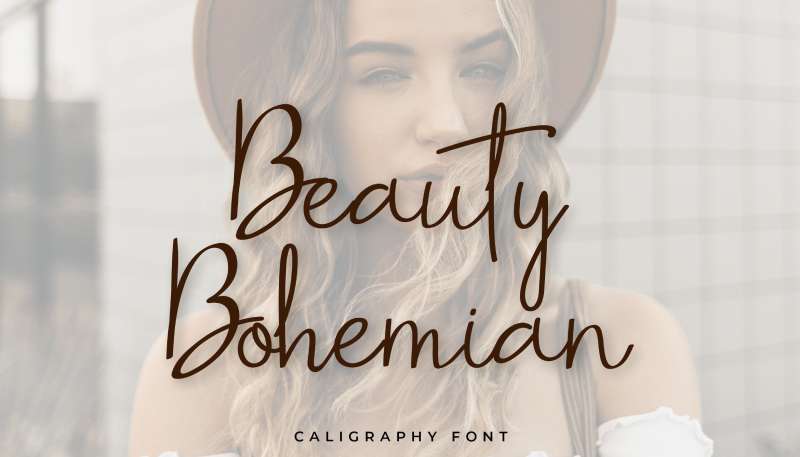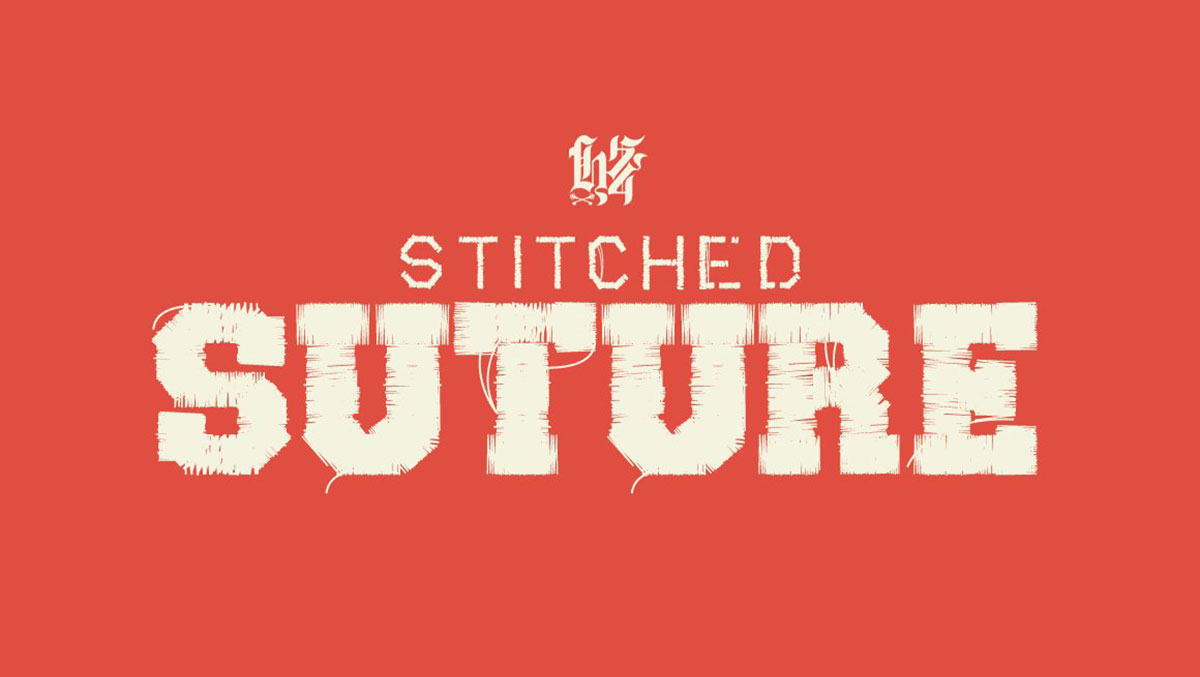
Stickerei verwandelt das Gewöhnliche in Kunst; der richtige Faden, ein Hauch von Kreativität, und voilà, ein Meisterwerk eingraviert in Stoff.
Aber was haucht wirklich Leben in Ihre Stickarbeiten ein? Die besten Schriftarten für Stickereien. Sie sind nicht nur Buchstaben; sie sind die stillen Botschafter Ihrer Marke, die unausgesprochenen Erzähler Ihres Handwerks.
In diesem Schatz an Texten liegt ein Rätsel für Designer – eine Schriftart zu wählen, die die Eigenheiten des Mediums ergänzt.
Ob Sie mit PES-Formaten digitalisieren oder von Hand einfädeln, der Weg vom Bildschirm zum Stoff ist voller Entscheidungen.
Fadengewicht, Spannungseinstellungen, der Stabilisator für Schriftstickerei – jedes Element ist eine Note in dieser visuellen Symphonie.
Dieser Artikel wird die Geheimnisse der Monogrammschriften lüften, sich tief in die Sticksoftware für Buchstaben einarbeiten und die Nadelauswahl für ein tadelloses Finish herausarbeiten.
Sie stöbern nicht nur in einer Liste; Sie schaffen ein Erbstück des Wissens, reihen ein Vermächtnis aus lesbaren, schönen Zeilen aneinander. Bereit für die Symphonie der Stiche zu beginnen?
Arten von Schriftarten geeignet für Stickereien
| Beste Schriftarten für Stickereien | Lesbarkeit | Stichart | Beste Verwendung | Anmerkungen |
|---|---|---|---|---|
| Bodoni Poster | Hoch | Satin/Stamm | Großer Text, Monogramme | Fett, gut verteilt, modernes Gefühl |
| Arial Black | Hoch | Satin/Füllung | Kühne Aussagen | Sehr klar und lesbar, gut für alle Größen |
| Impact | Hoch | Satin/Stamm | Überschriften, Zahlen | Enge Räume, benötigt sorgfältige Handhabung in kleinen Größen |
| Wein Monogramm | Mittel | Satin/Stamm | Personalisierung, Monogramme | Elegant, erfordert präzises Sticken aufgrund von Kurven |
| Kreis Monogramm | Mittel | Satin/Stamm | Monogrammierung | Bietet ein traditionelles und formelles Aussehen |
| Block Monogramm | Hoch | Satin/Füllung | Monogramme, Etiketten | Klassischer Look, gut für verschiedene Stoffarten |
| Klassisches Monogramm | Mittel | Satin/Stamm | Monogramme, Personalisierung | Zeitloser Stil, möglicherweise nicht ideal für kleinen Text |
| Genäht | Hoch | Füllung/Satin | Lässige oder skurrile Designs | Gut für größere Designs, der ‚genähte‘ Look ist eine Stilwahl |
| Kreuzstich Kursiv | Mittel | Kreuzstich | Dekorativ, altmodischer Look | Speziell für einen Kreuzsticheffekt designed |
| Familienheim | Mittel | Satin/Stamm | Heimdekoration, Quilts | Heimelig und malerisch, kann klein sein |
| Cattieshine | Niedrig | Satin/Stamm | Dekorativ, künstlerische Designs | Kann aufgrund seiner dekorativen Natur hohe Präzision erfordern |
Serifenschriften
Serifenschriften sind klassisch. Sie sind wie dieser alte Plattenspieler, der nie aus der Mode kommt. Sie wissen, diejenigen mit diesen kleinen Linien oder Strichen am Ende der Buchstaben? Sie bringen einen Hauch von Eleganz und Raffinesse in Ihre Stickerei. Wenn Sie über Stickerei-Schriftstile nachdenken, sind Serifenschriften wie Times New Roman oder Baskerville wie die Beatles der Schriftwelt – zeitlos und universell ansprechend.
Aber denken Sie daran, nicht alle Serifenschriften sind gleich, wenn es um Stickereien geht. Der Schlüssel liegt im Detail. Einige, wie Georgia oder Garamond, funktionieren wunderbar auf einer Vielzahl von Stoffen, während andere, wie Palatino, besser für bestimmte Stickprojekte geeignet sind. Es ist wie die richtige Weinwahl zu Ihrem Essen – die richtige Wahl kann Ihr gesamtes Erlebnis aufwerten.
Serifenlose Schriften
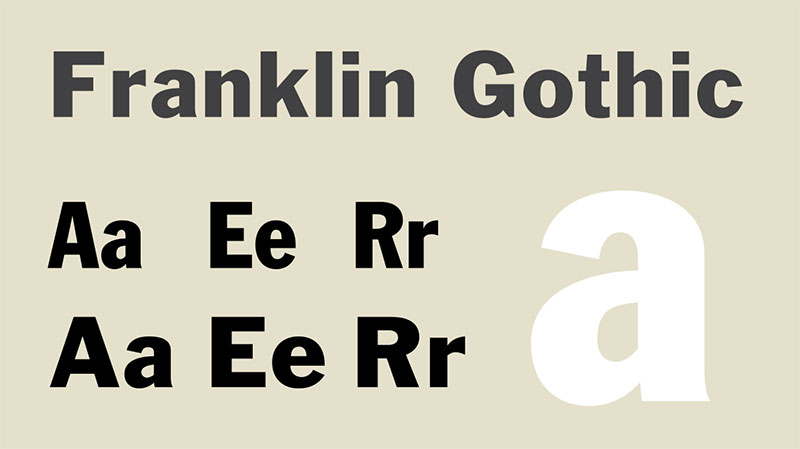
Weiter geht es mit serifenlosen Schriften. Diese sind das moderne Yin zum Serif-Yang. Serifenlose Schriften verzichten auf diese kleinen Linien für einen saubereren, minimalistischeren Look. Denken Sie an Helvetica oder Arial, sie sind wie die Spotify-Playlist, die alles frisch und modern hält.
Serifenlose Schriften sind fantastisch, wenn Sie Ihrer Stickerei ein zeitgenössisches Gefühl verleihen wollen. Sie sind auch ein Geschenk des Himmels, wenn Sie mit kleineren Texten arbeiten, da das Fehlen von Serifen sie auf einen Blick lesbarer macht. Schriften wie Futura oder Franklin Gothic eignen sich perfekt für Stücke, die Informationen schnell und stilvoll vermitteln müssen.
Schreib- und Kursivschriften
Jetzt sprechen wir über Schreib- und Kursivschriften. Das sind die Schriften, die wie eine schöne Melodie über Ihren Stoff fließen. Sie sind der handgeschriebene Liebesbrief in einer Welt voller E-Mails und Textnachrichten. Schreibschriften wie Edwardian Script oder Brush Script verleihen jedem Stickprojekt eine persönliche, handgemachte Note.
Aber hier ist ein Profi-Tipp: Schreib- und Kursivschriften erfordern etwas mehr Fingerspitzengefühl und Geduld. Die komplizierten Schlaufen und Wirbel von Schriften wie Monotype Corsiva oder Mistral können etwas schwierig zu sticken sein, aber das Endergebnis ist es wert. Es geht darum, diese Eleganz und den Fluss einzufangen und jedes Wort in ein Kunstwerk zu verwandeln.